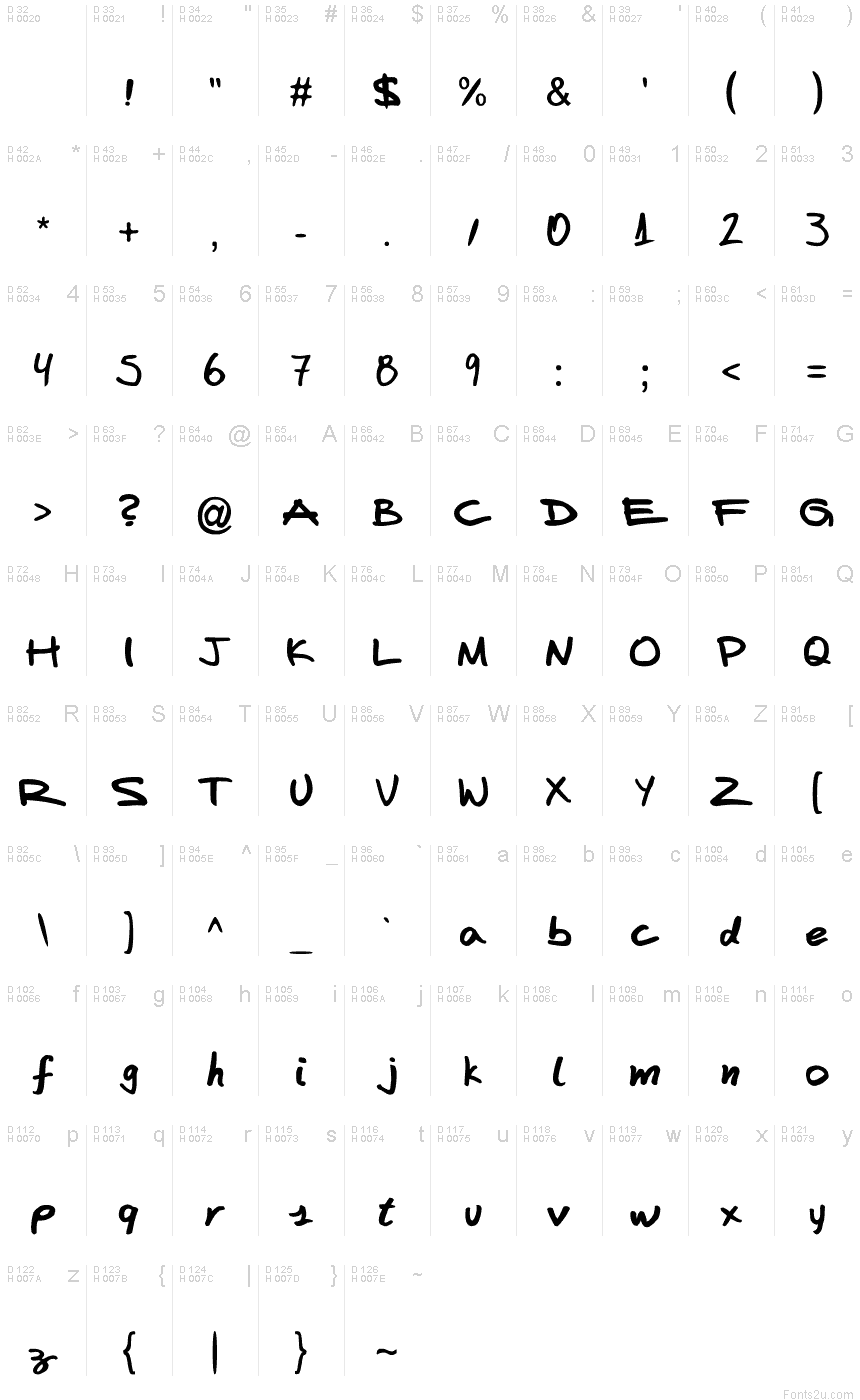
Fafers je bezplatné písmo ve stylu psaném fixou, s uvolněným, městským nádechem. Písmena působí jako rychle načrtnutá tlustým fixem, kombinují široké vodorovné tahy, zaoblené rohy a lehce nerovnoměrné spoje, díky čemuž design působí ležérně, nikoliv učesaně.
Hodí se na plakáty, grafiku s tématikou skate či hudby, obálky zinů, návrhy log a výrazné nadpisy na sociálních sítích, kde potřebujete bezplatný font, který vypadá jako ruční práce, a ne jako výstup ze softwaru. Protože jsou tvary robustní a otevřené a linka se lehce vlní, dobře funguje i v krátkých titulcích, na obalech a u názvů, které vyžadují pohodovou, ručně kreslenou atmosféru.
FAFERS Handwriting Font